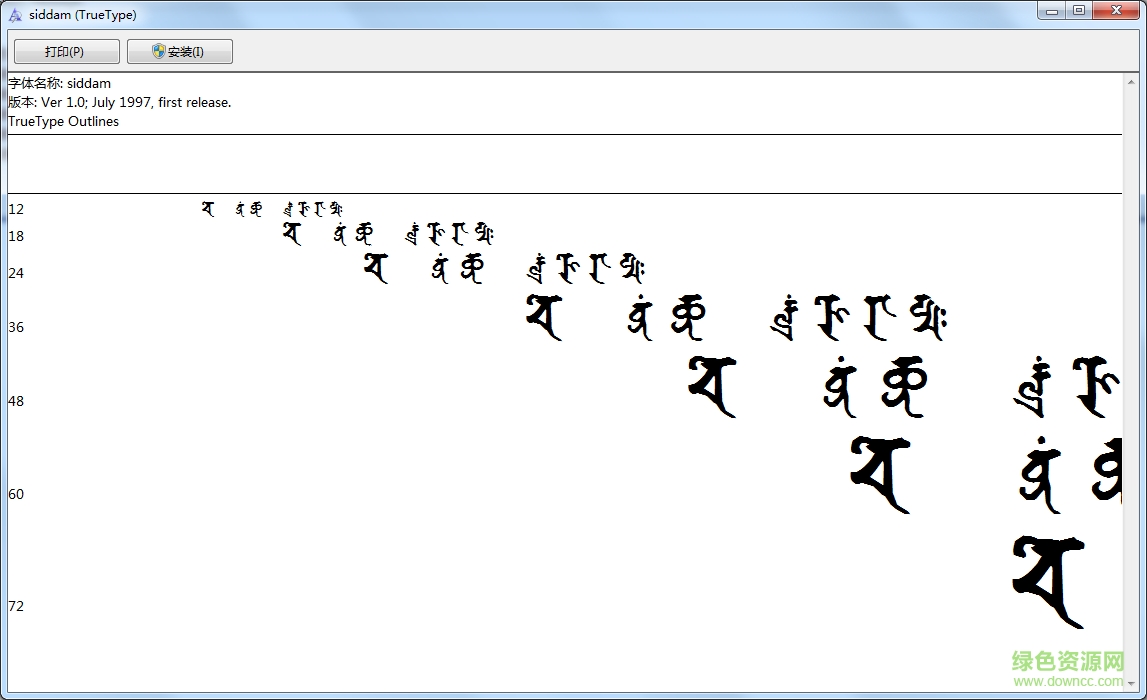
梵文悉曇體
悉曇梵文字體是一款非常好用的梵文字體,梵文在佛教中使用非常的廣泛,字體非常的剛勁有力,也非常的漂亮,歡迎有需要的朋友到綠色資源網(wǎng)下載使用!
悉曇梵字,也是梵文重要的組成部分,佛教中用來觀想,大多用的都是悉曇梵字,在日本東密的總本山高野山,就流傳著世界上最為標(biāo)準(zhǔn)的悉曇梵文,從唐代唐密傳入日本,至今依然留傳著,屬于最古老的悉曇梵字!